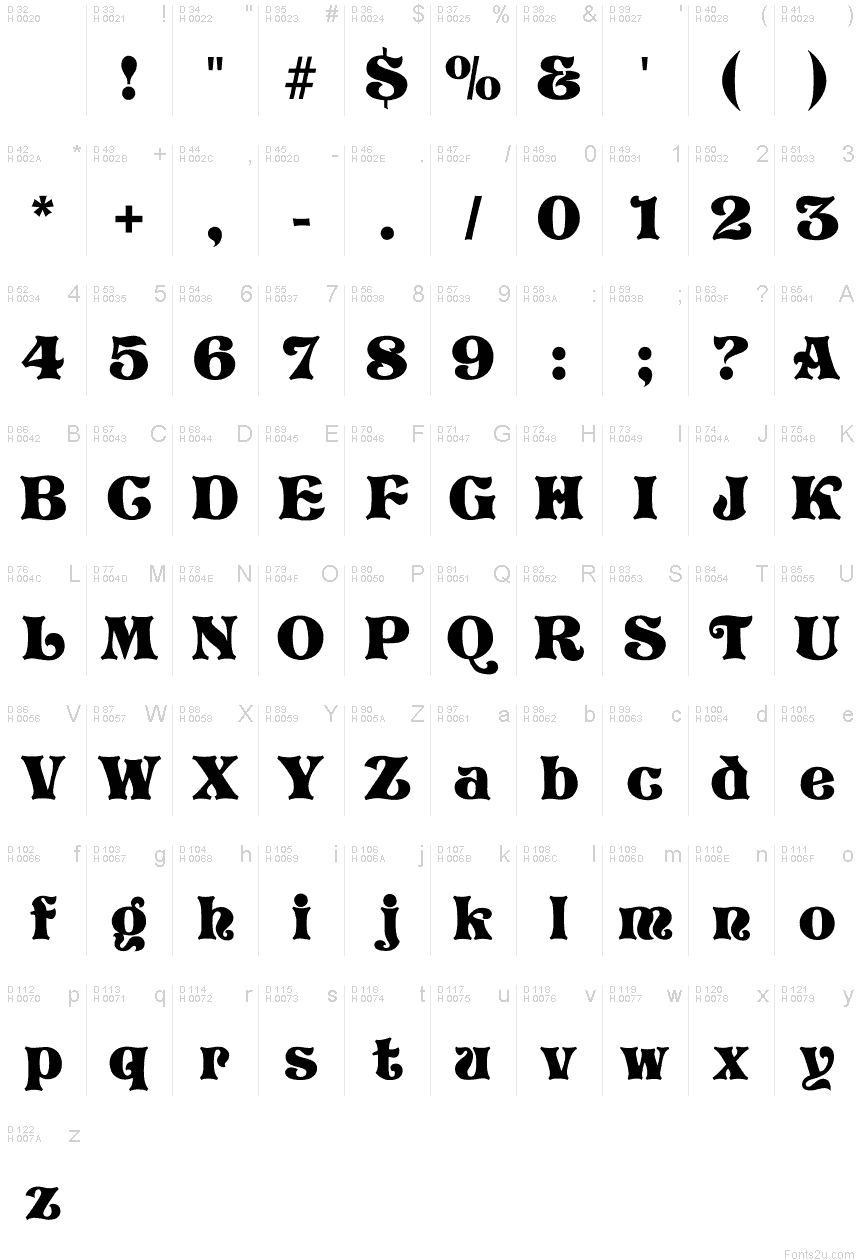
Storybook to darmowy, retro font displayowy stworzony w programie Fontographer 3.5. Liternictwo rodem z baśni przyciąga wzrok dużymi, obłymi krzywymi oraz miękkimi, wyrazistymi szeryfami. Znaki łączą w sobie średniowieczny klimat z klimatem lat 70., a kroplowate łączenia, zawijasy i zaokrąglona waga sprawiają, że całość jest zabawna, a nie poważna.
Font świetnie sprawdzi się na okładkach książek, nagłówkach plakatów, opakowaniach butikowych, szyldach kawiarni i tytułach, gdzie potrzebna jest odrobina folkloru bez popadania w czarną gotykę. Dzięki szerokim łukom i zawiniętym zakończeniom, krój ten dobrze wygląda w krótkich napisach brandingowych, na otwarciach rozdziałów oraz w inicjałach typu monogram, zwłaszcza gdy chcesz, aby tekst brzmiał jak opowieść, a nie tylko złożony napis.